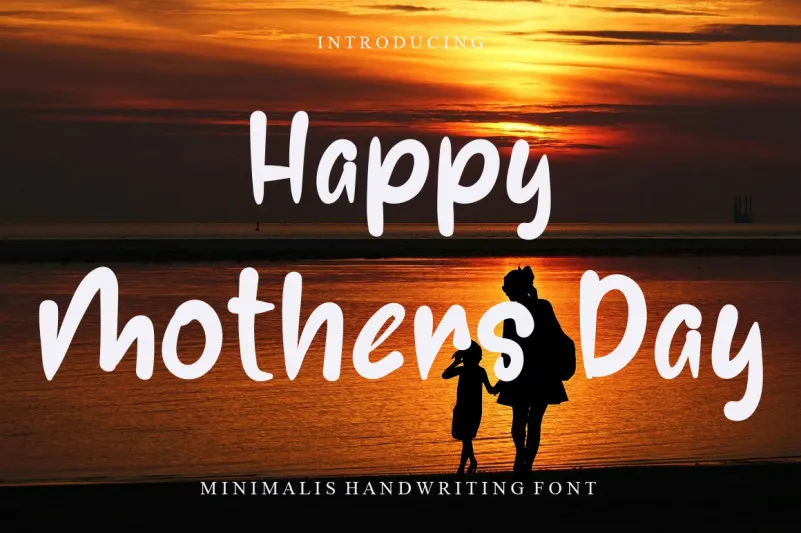
Happy Mothers Day Font – Download Grátis
Esta fonte é perfeita para quem está buscando uma maneira criativa e relaxada de celebrar a Mães neste dia especial. Com seu estilo casual e agradável, Happy Mothers Day Font é uma escolha ideal para qualquer projeto que você esteja trabalhando. Seja um cartaz com letras grandes ou um texto personalizado no bebê da sua mãe, essa fonte será uma ótima adição à sua biblioteca de fontes. Proporcionando a sensação de conforto e relaxamento, ela encaixa-se perfeitamente em criações de design gráfico que exigem leveza. O designer LevinCreative criou um verdadeiro acréscimo para qualquer obra que utilize essa fonte, sejam cartazes publicitários ou designs personalizados destinados a serem compartilhados online ou impressos. Para as mães especiais da sua vida, seja alguém ao seu lado na maternidade, uma amiga querida ou simplesmente aquela pessoa especial em sua vida, este é um presente que ela certamente apreciará. Com apenas um clique e algumas letras, transforme qualquer projeto em algo significativo e único para as mães especiais da sua vida.